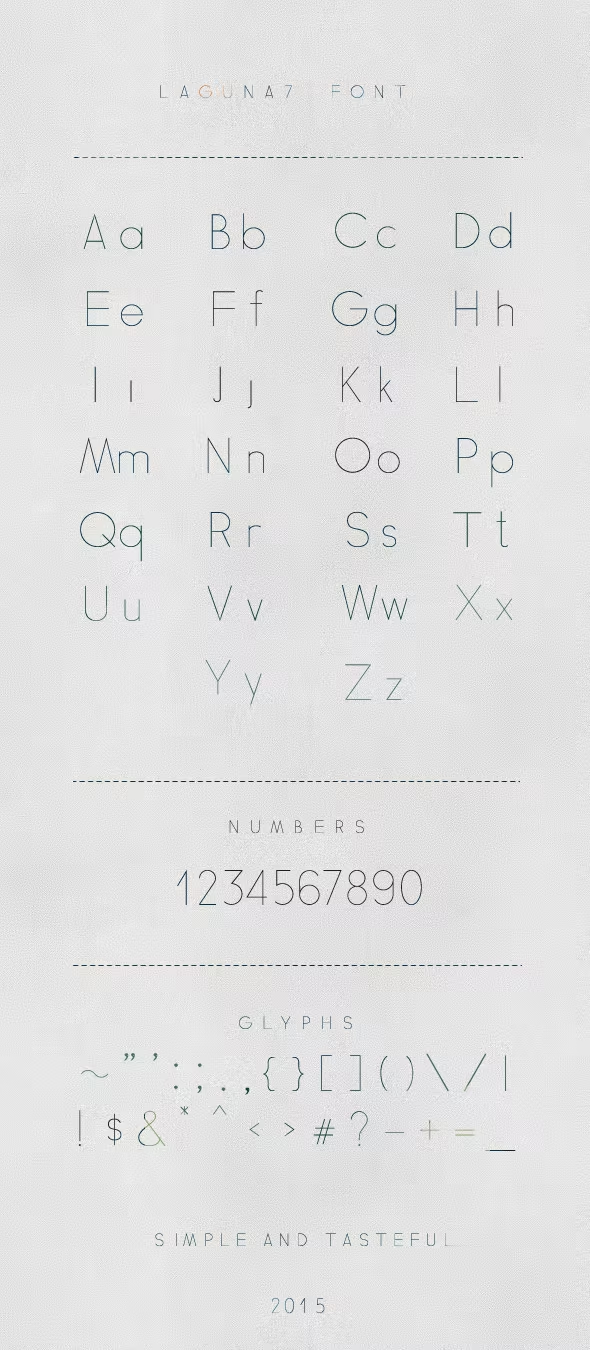
Laguna7 Font
Description de Laguna7 Font
Cette police est destinée à être utilisée dans les affiches de marque, de publicité, de typographie, etc. Il s’agit d’une simple police à espacement fixe au format OpenType, qui comprend :
-Lettres ABCDEFGHIJKLMNOPQRSTUVWXYZabcdefghijklmnopqrstuvwxyz
-Numéros 1234567890
-Glyphes ~!#$ ^x%x *()[]{}|:;”’<>,.?/+-_=% et autres